Google Fonts тепер підтримує іконки з відкритим вихідним кодом, починаючи з набору іконок Material Design. Це однозначно хороші новини.
Оскільки іконографія стала центральною частиною будь-якої дизайн системи, Material Design підтримує набір з більш ніж 2000 різних іконок, доступних в п’яти стилях. А оскільки типографія і іконографія так тісно пов’язані, Google тепер додає іконки в Google Fonts на fonts.google.com/icons.
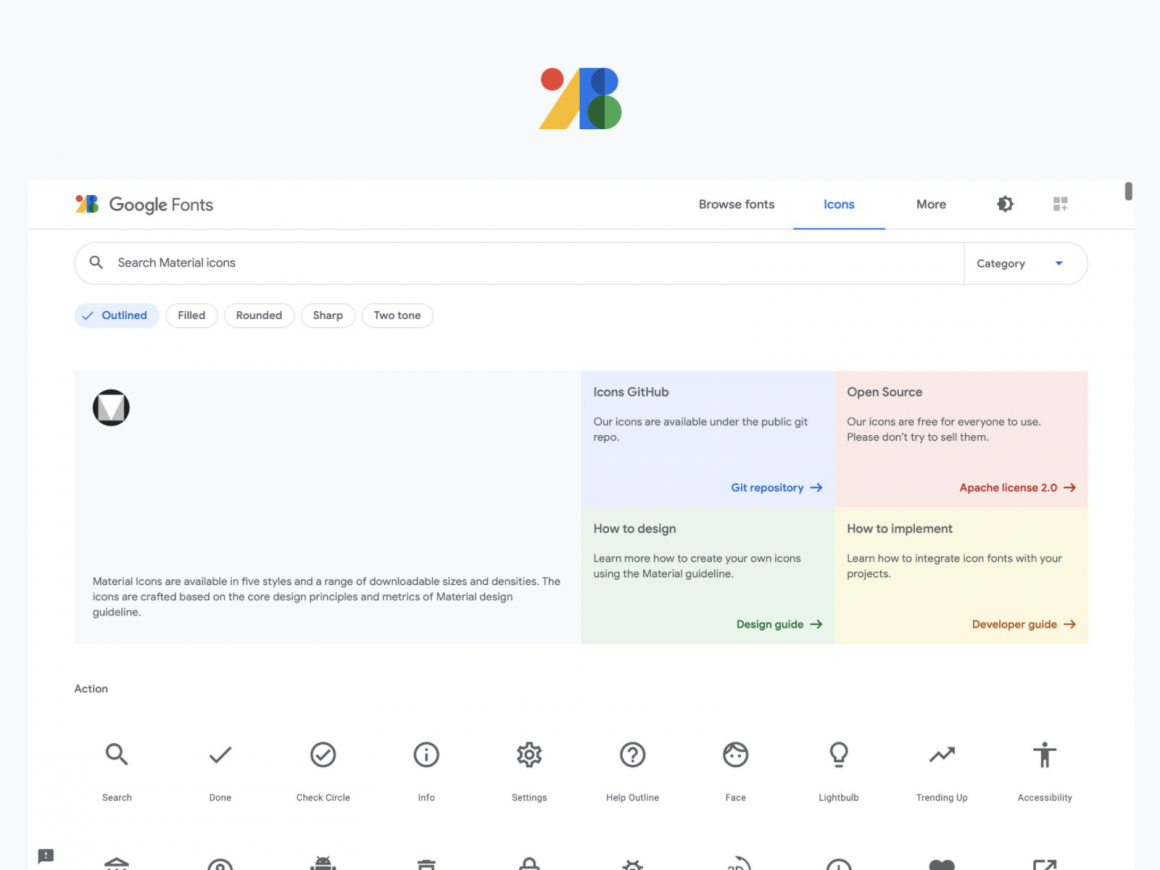
«Іконки в матеріальному дизайні — це чудові, красиво оформлені базові іконки, доступні в різних стилях (Outlined, Filled, Rounded, Sharp, Two tone). І вони доступні для завантаження або використання в якості веб-шрифту через наш API.
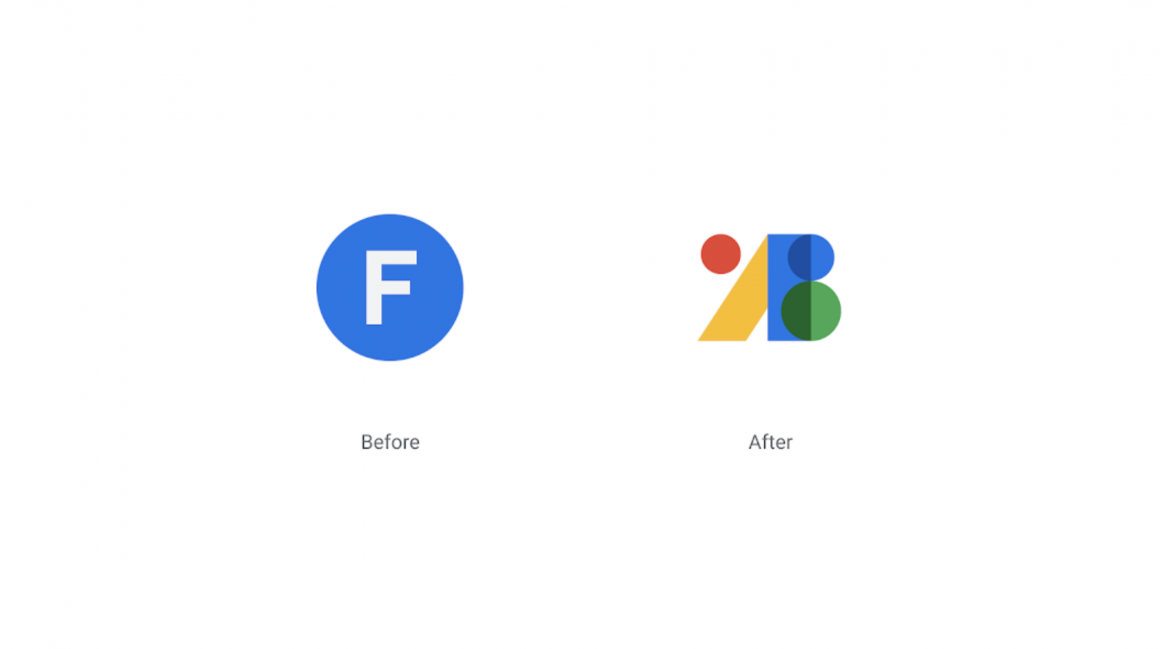
Щоб відсвяткувати цю віху, ми також створили абсолютно новий логотип для самого Google Fonts. Ми вирішили ребрендовані нашу монограму «F» і перетворити її в щось нове, що віддзеркалює суть продуктів і послуг, пропонованих Google Fonts.
На перший погляд новий логотип може здатися абстрактними формами, що складаються з кіл і прямокутників, але при більш уважному розгляді можна помітити кілька змішаних разом гліфів та іконок. Новий візуальний знак дає нам велику гнучкість дизайну, а також дає натхнення для загального зовнішнього вигляду користувальницького інтерфейсу, щоб краще відобразити наше бачення майбутнього шрифтів.»